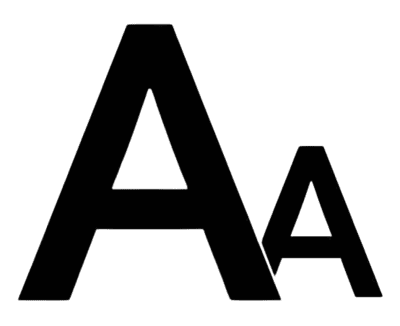
Apa Itu Font Size – Kita sering menjumpai berbagai jenis ukuran pada teks, sebenarnya apa itu font size? Font size atau ukuran font adalah dimensi atau skala dari huruf huruf dalam teks. Font size memengaruhi seberapa besar atau kecil teks terlihat pada halaman atau layar.
Apa Itu Font Size
Pengertian Font Size
Ukuran font itu sebenarnya menunjukkan seberapa besar atau kecil hurufnya dalam tulisan, diukur dalam poin atau piksel. Jadi, ukuran font ini penting banget buat memastikan tulisan kita bisa dibaca dengan jelas dan sesuai dengan yang kita inginkan. Font size memainkan peran penting dalam desain grafis dan tipografi karena dapat memengaruhi keterbacaan, hierarki visual, dan keseluruhan estetika dari suatu dokumen atau desain. Dalam pemrograman web, ukuran font juga dapat diatur dengan menggunakan unit seperti em atau rem. Pemilihan ukuran font yang tepat memastikan bahwa teks dapat terbaca dengan baik dan sesuai dengan tujuan desain yang diinginkan.
Jenis Jenis Font Size
- Small (kecil)
- Medium (sedang)
- Large (besar)
- Extra Large (Sangat Besar)
- Heading Sizes (Ukuran Heading)
- Body Text Size (Ukuran Teks Tubuh)
Fungsi
- Membantu pembaca dengan mudah membaca dan memahami informasi yang di sajikan.
- Menciptakan hierarki visual dalam desain.
- Ukuran font yang besar dapat digunakan untuk menekankan pesan atau elemen tertentu dalam desain, seperti judul atau tagline. Ini membantu pesan tersebut menonjol dan mudah dicatat.
- Membantu membedakan jenis teks, seperti judul, heading, subheading, dan teks tubuh.
- Pemilihan font size yang sesuai dengan gaya dan tujuan desain dapat meningkatkan tampilan visual secara keseluruhan.
- Font size yang konsisten di seluruh desain memberikan kesan yang teratur dan profesional.
Dengan demikian, font size merupakan pilihan desain yang memiliki dampak signifikan dalam menyampaikan pesan. Kemampuannya membimbing mata pembaca, menonjolkan informasi, dan menciptakan struktur visual menjadikannya elemen tak terpisahkan dalam dunia tipografi. Pemilihan ukuran font yang bijak tidak hanya memastikan pesan terbaca dengan jelas, tetapi juga menciptakan tata letak yang menarik dan terstruktur.